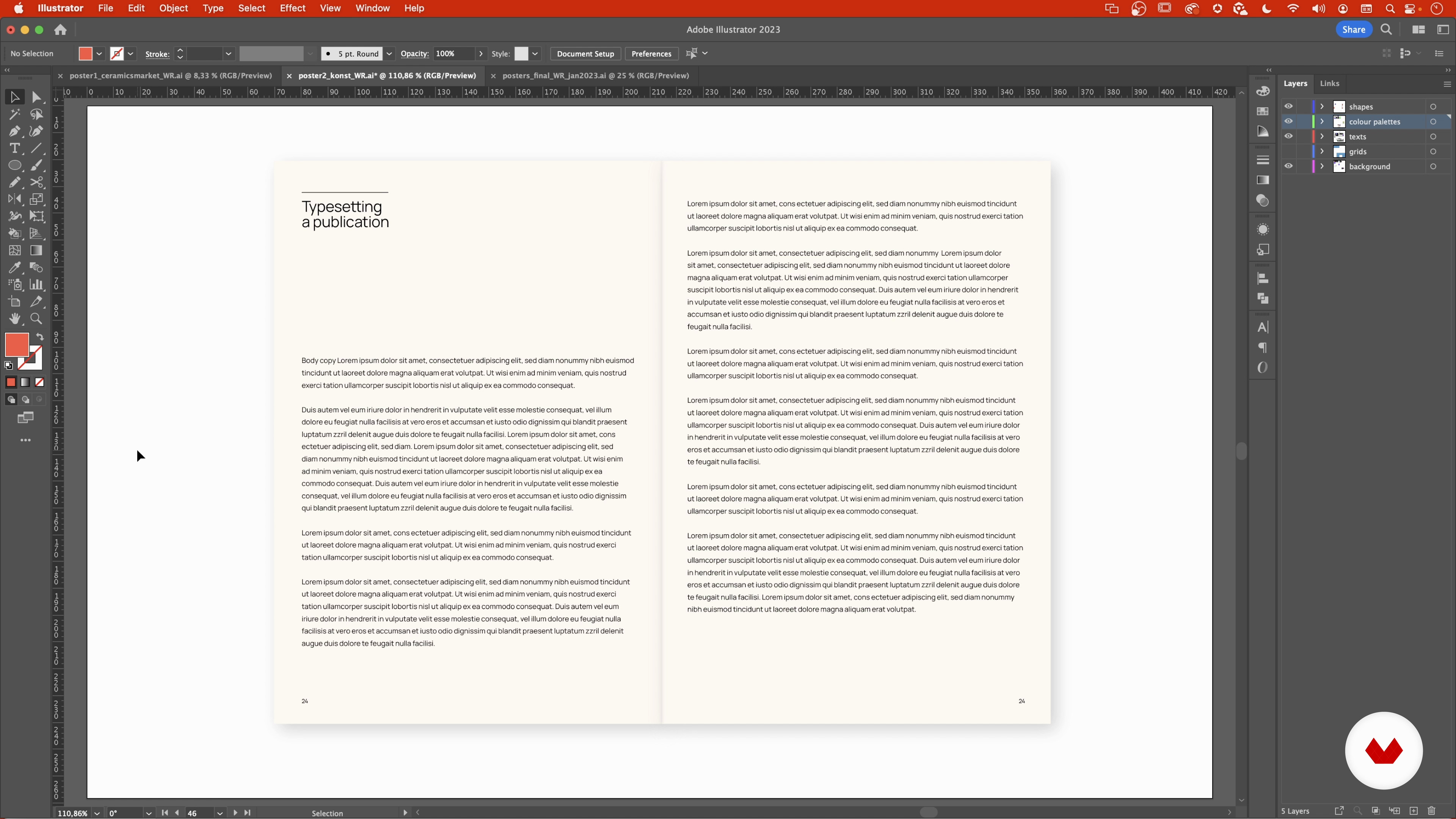
Composição
Sobre a videoaula: Composição
Visão geral
“Usando o conteúdo do pôster 2, aprenderemos o básico dos menus Caractere e Parágrafo. Iremos compor o texto dentro da composição, certificando-nos de que ele estabeleça a hierarquia tipográfica correta e seja adequado para um concerto. ”
Nesta videoaula, Weronika Rafa aborda o tópico: Composição,que faz parte do curso online da Domestika: Introdução ao design gráfico para quem não é designer. Descubra a arte do design e crie pôsteres incríveis usando cor e tipografia..
Transcrição parcial do vídeo
“Nesta lição. abordaremos a composição tipográfica com os esboços do pôster 2. concerto Supernova para Kunst. Composição tipográfica nada mais é do que arranjar a tipografia de forma a torná-la legível e funcional ao usuário. Então. eu. falo sobre composição tipográfica. geralmente estou pensando em fragmentos maiores de texto. De forma semelhante ao que começamos a fazer aqui com cópia de corpo. Vamos voltar para esboços de pôster por um momento e usarei o conteúdo do pôster 2 para isso. Felizmente. com o pôster sendo uma aplicação que mistura arte e design. Em muitos casos. não haverá tant...”